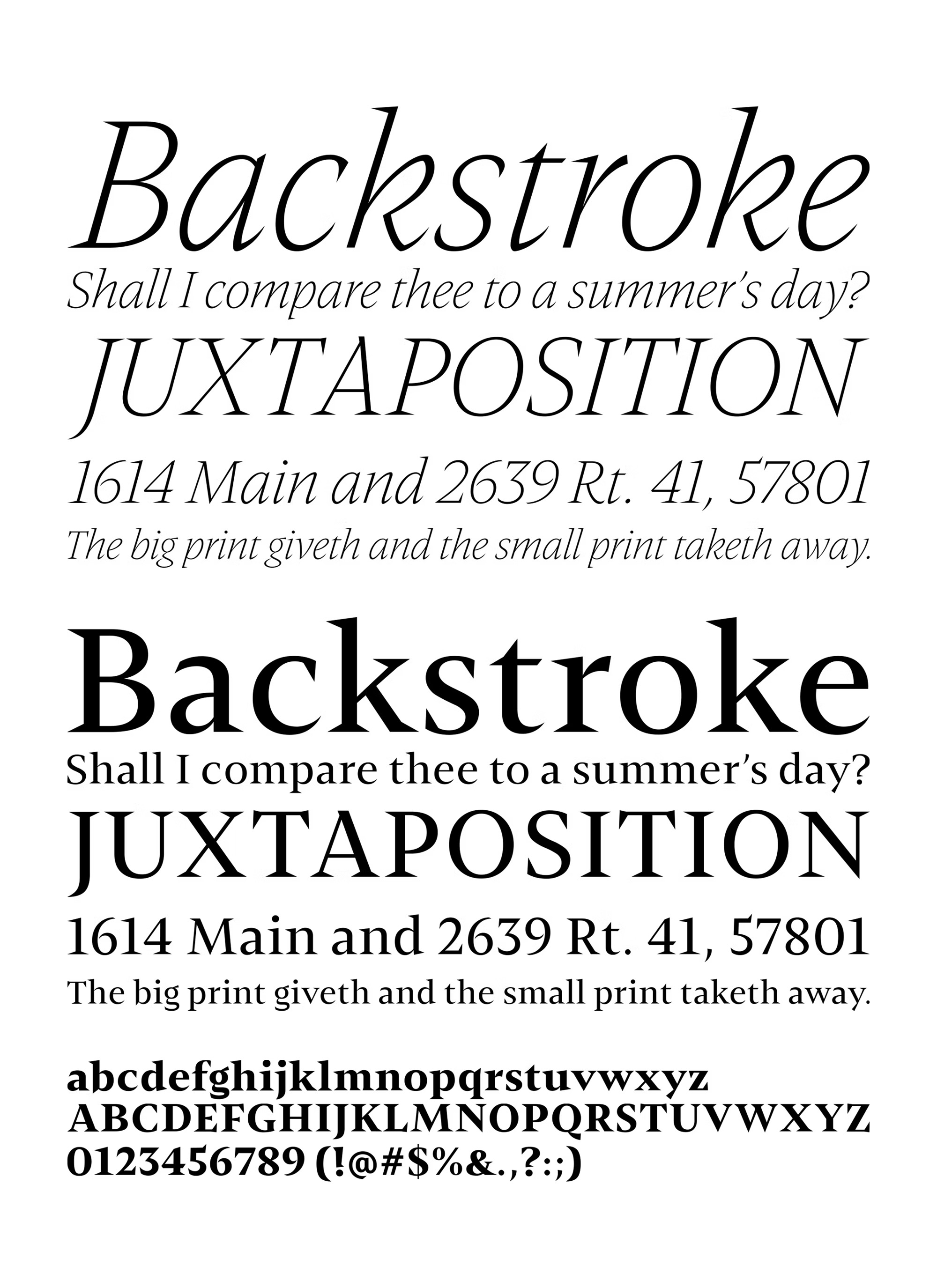
| Año | 2017 |
| Créditos | Sergio Leiva Whittle, Rodrigo López Fuentes |
| Descripción | Nikola es una tipografía de texto que ofrece una amplia gama de posibilidades. Mientras que sus grosores regular y medio se optimizaron especialmente para un rendimiento máximo, se equilibraron para una excelente legibilidad y se elaboraron cuidadosamente para transmitir un toque de tradición a textos extensos, sus grosores extremos, en cambio, se diseñaron para un uso más expositivo y, gracias a la flexibilidad que ofrecen sus numerosas alternativas, florituras, cartuchos decorativos, bordes y ornamentos, pueden ofrecer al texto una inflexión vintage, fiable, dinámica, sofisticada e incluso divertida. |
| Clasificación | Texto |
| Fundidora | Untype foundry |